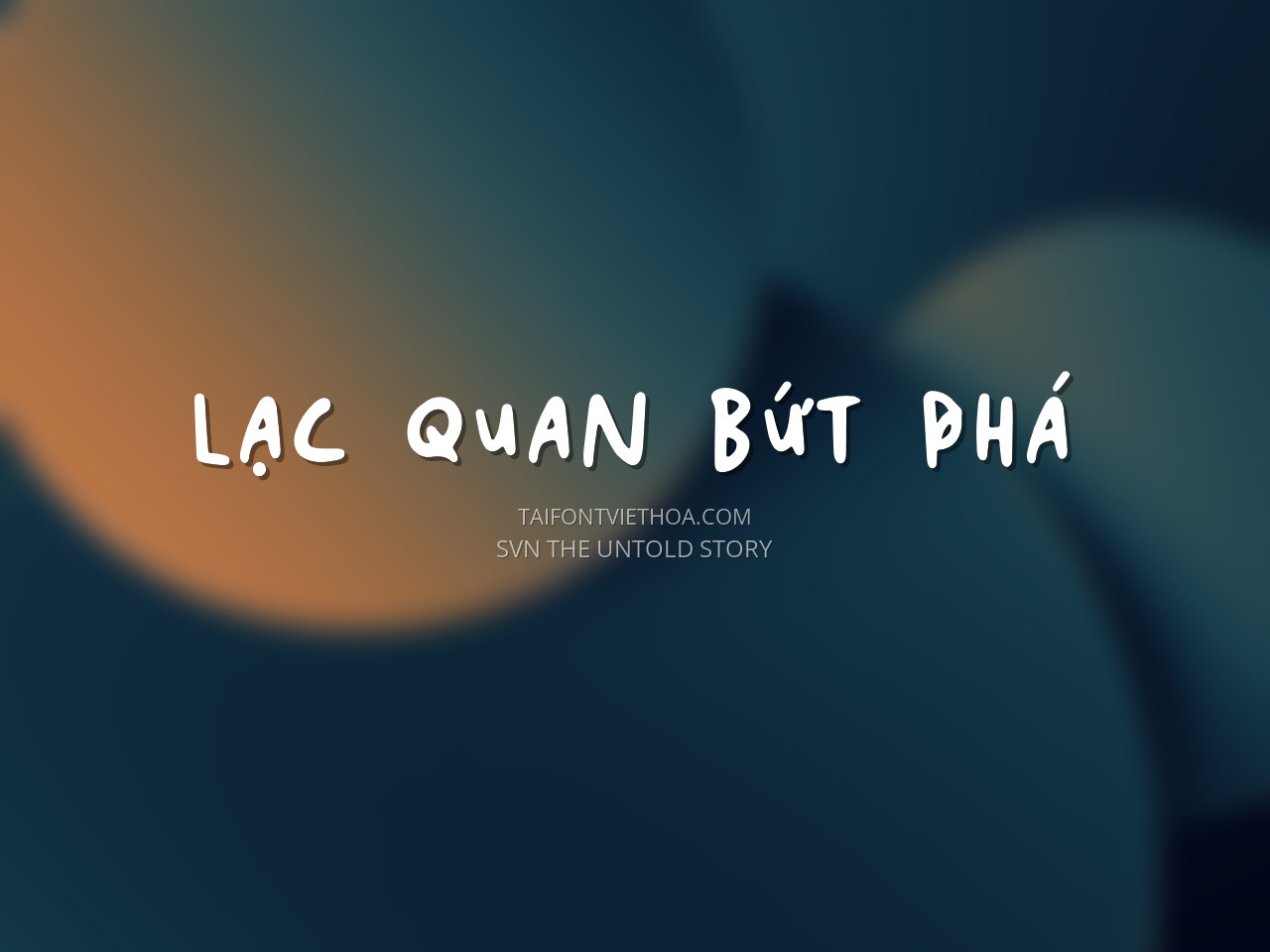
Font việt hóa SVN The Untold Story
Giới thiệu về The Untold Story – Font handwritten sáng tạo, cảm xúc
The Untold Story (tên gốc: The Untold Story Typeface) là phông chữ viết tay (handwritten) độc đáo được phát triển bởi Letterhend Studio(Indonesia) và phát hành lần đầu trên Creative Market năm 2020. Font lấy cảm hứng từ những nét bút ghi chú tự nhiên, phóng khoáng nhưng vẫn gọn gàng, giúp truyền tải trọn vẹn cảm xúc cá nhân cho từng thiết kế. Bản quốc tế hỗ trợ trên 60 ngôn ngữ Latin, tích hợp nhiều glyph đặc biệt, ký tự số, ligatures và alternates – phù hợp đa dạng dự án từ digital đến in ấn truyền thống.
Phiên bản SVN The Untold Storyđã được STYLEno.1 FontsViệt hóa đầy đủ: bổ sung dấu tiếng Việt, căn chỉnh kerning tối ưu và hinting mượt mà để font hiển thị sắc nét trên cả màn hình và khi in ấn. Đội ngũ taifontviethoa.comđã kiểm thử thực tế trên nhiều phần mềm thiết kế như Photoshop, Illustrator, Canva, CorelDRAW…, đảm bảo font không lỗi dấu, không vỡ nét dù dùng ở kích thước nhỏ hay lớn. Nhờ đó, The Untold Story Việt hóa giúp mọi designer Việt dễ dàng sáng tạo nội dung, làm nổi bật cá tính riêng trên từng dự án thực tế.
Đặc điểm thiết kế, ứng dụng và ngành nghề phù hợp
The Untold Story thuộc nhóm viết tay (handwritten)với các nét chữ mềm mại, có độ nghiêng nhẹ và nhịp điệu tự nhiên, tạo cảm giác thân thiện, gần gũi. Các ligatures và alternates cho phép tùy biến linh hoạt, phù hợp cho thiết kế tiêu đề, logo cá nhân, ghi chú, quotes truyền cảm hứng, hoặc các ấn phẩm truyền thông cần nhấn mạnh tính cá nhân hóa. Font còn đặc biệt hiệu quả khi sử dụng trên thiệp mời, sổ tay, poster nghệ thuật, hay nhãn sản phẩm handmade.
The Untold Story là lựa chọn hoàn hảo cho ngành sáng tạo, quảng cáo, handmade, thời trang, beauty, spa, tổ chức sự kiện… Khi kết hợp cùng font sans-serif, The Untold Story sẽ giúp tổng thể thiết kế mềm mại, nổi bật và mang dấu ấn cá nhân hóa. Tải ngay bản Việt hóa tại taifontviethoa.com để trải nghiệm trọn bộ glyph cho mọi dự án sáng tạo của bạn.